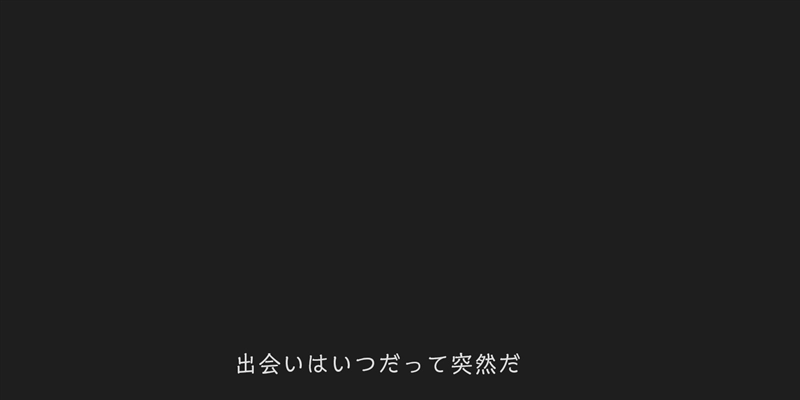
トーキング フォントの作例
トーキング フォントの作例です。
字幕にも使える手描き感のあるデザインのフォントです。
字幕系フォントの中ではやや活字感のあるデザインの書体といった印象です。字幕よりも短文などの文章に合わせやすいデザインかもしれません。
標準の設定で文字間が少し広めになるため、単純に配置した状態でも読みやすい見た目になります。
トーキング フォントの作例:画像1